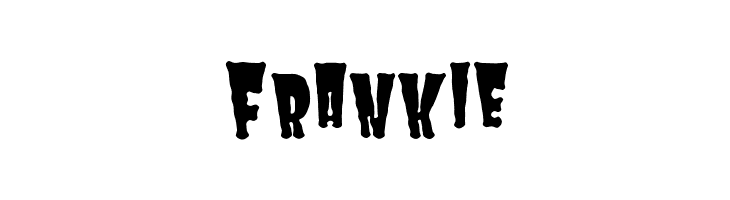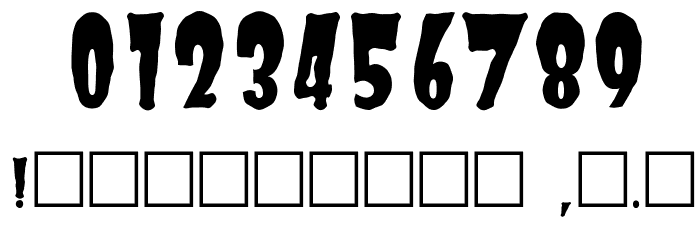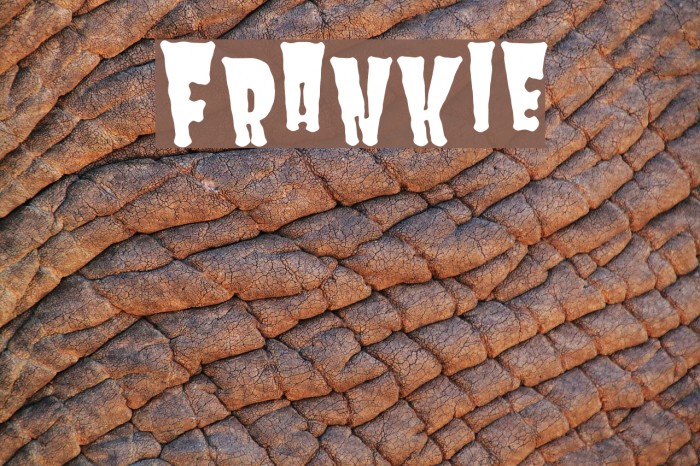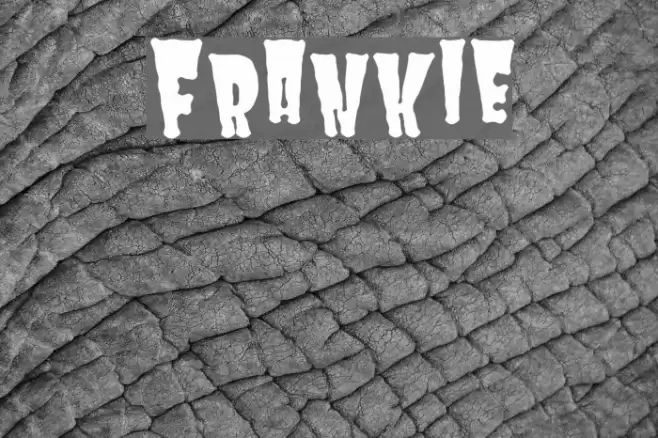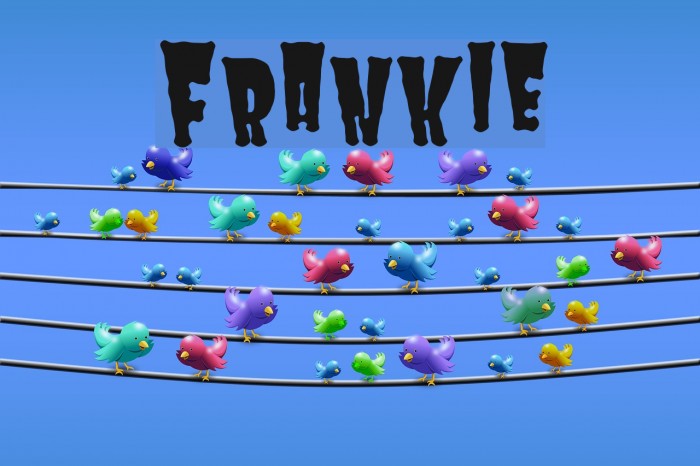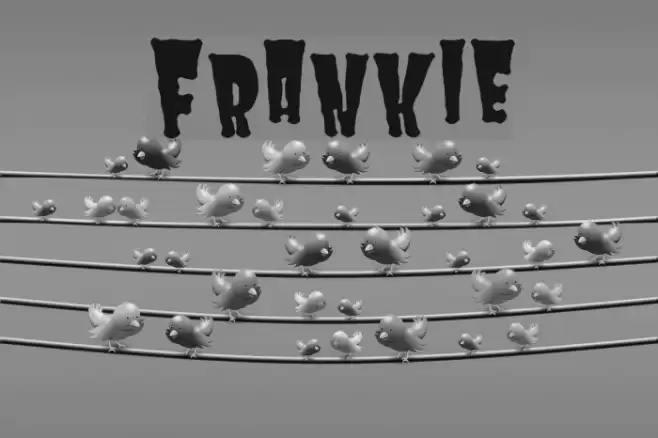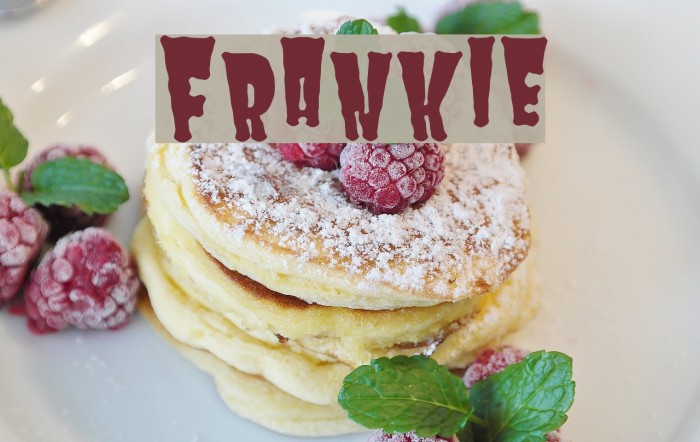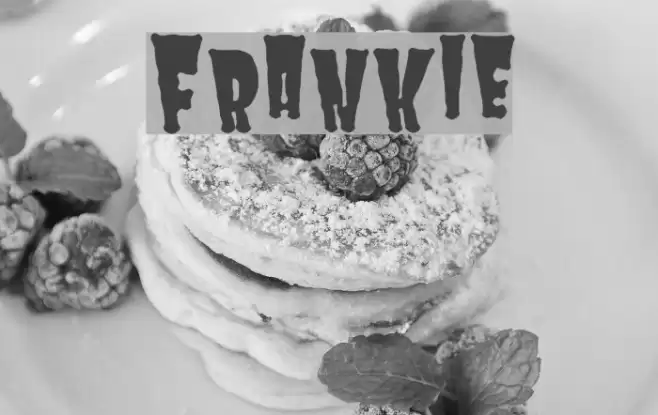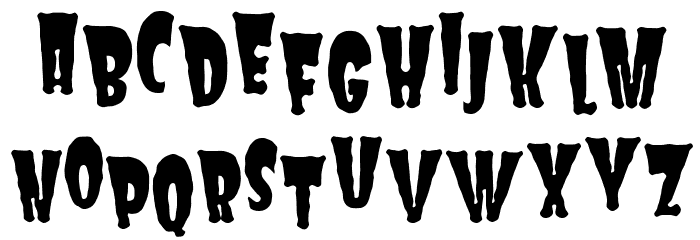
Frankie Font
| Общий стиль | Whimsical, Spooky, Playful |
| Рекомендуемые проекты | Perfect for Halloween designs, children's books, party invitations, and playful branding. |